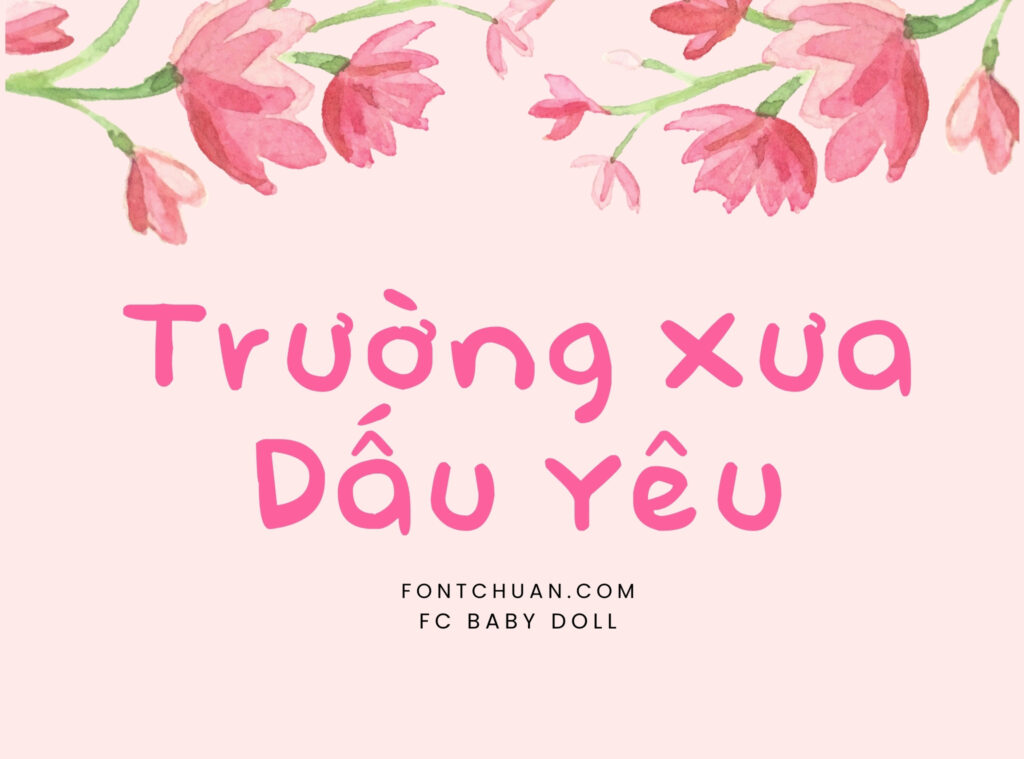
Font FC Baby Doll Việt Hóa
Baby Doll là một font chữ viết tay độc đáo, được thiết kế bởi Denise Bentulan và phát hành vào năm 2011. Với các nét chữ mềm mại và ngẫu hứng, Baby Doll mang lại cảm giác thân thiện và vui tươi, phù hợp cho các dự án thiết kế như thiệp mời, poster, tiêu đề và các ấn phẩm quảng cáo khác.
Font FC Baby Doll của team Font Chuẩn việt hóa để hỗ trợ tốt cho tiếng Việt nhưng lại Free vấn đề việt hóa, hỗ trợ tốt cho tiếng Việt, tiếng Anh và nhiều ngôn ngữ Latin khác, mở rộng khả năng ứng dụng cho nhiều dự án quốc tế.
Với cấu trúc chữ ngẫu hứng, độ dày đồng nhất và thiết kế tinh tế, Baby Doll phù hợp cho các thiết kế yêu cầu sự sáng tạo và thân thiện. Đặc biệt, font này thích hợp cho các ngành nghề như quảng cáo, thiết kế thiệp cưới và lĩnh vực giải trí, nơi cần sự kết hợp giữa thẩm mỹ độc đáo và chức năng truyền tải thông điệp.